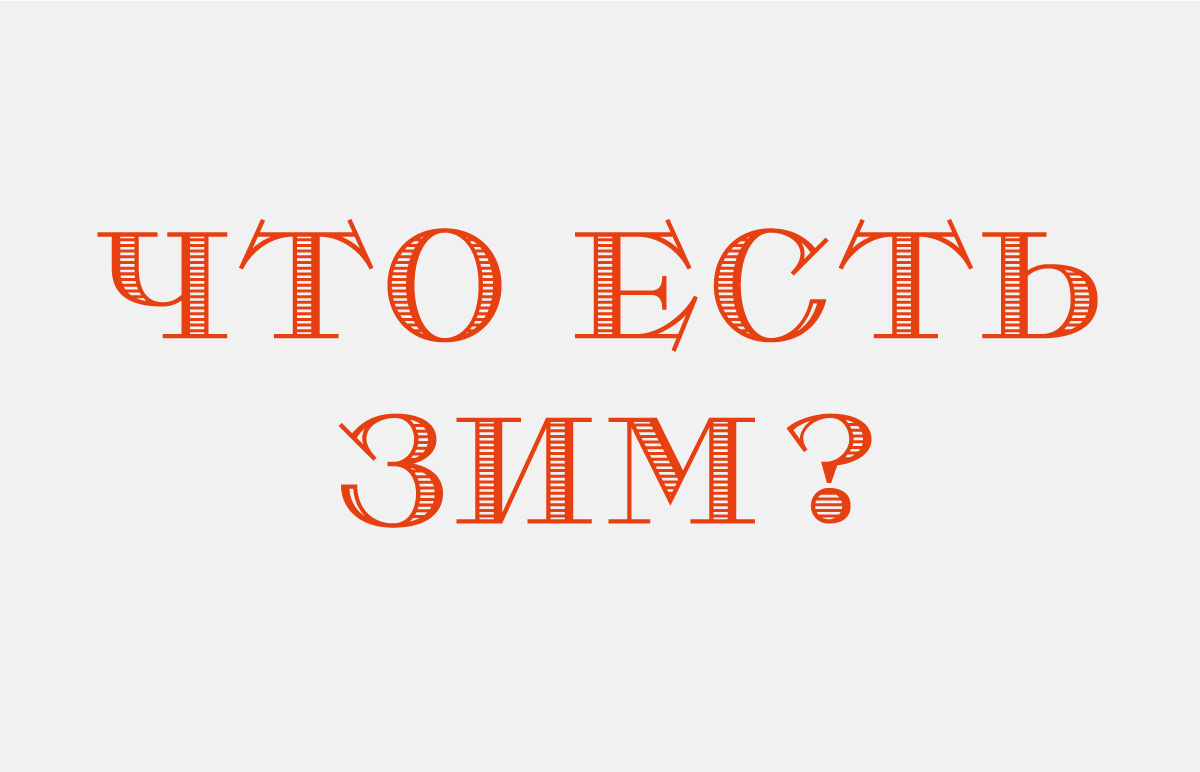
Конгрев как символ тирании
Книга Александра Лекае о легендарном детище Горьковского автомобильного завода — ГАЗ-12 «ЗИМ» — напоминает поэму, где всего с избытком: певучих строк о внешнем виде представительского автомобиля, исторического пафоса, вставных новелл о вожде, который, как и подобает истинному тирану, то казнит, то милует в зависимости от расположения духа. Однако, преодолевая пафос, постепенно приходишь к главному: это книга о времени и людях, которые верили в свою судьбу.
печатляющий красный том повествует не только о выдающемся советском инженере-конструкторе Андрее Александровиче Липгарте, о драматической истории создания автомобиля в жёстких условиях войны и мира, больше похожего на войну. Главным образом он рассказывает об одержимости ремеслом. Дело, в конце концов, не в блестящем, похожем на майского жука ЗИМе (который и сегодня вызывает восхищение не только у коллекционеров и любителей техники), а в той правде, которая через десятилетия оказалась выше любых политических вихрей, — правде последнего винтика в автомобиле или самого незначительного (на взгляд обывателя) узла на чертёжной кальке, над которым трудились и орденоносный конструктор Липгарт, и гениальные инженеры Борис Акимович Дехтяр и Владимир Никитич Носаков, и все рабочие завода.
В этом свете дизайн книги выглядит старательно выстроенной декорацией, призванной помочь читателю стать сопричастным тому времени. Собственно, такова и была идея издателя. В понимании Александра Лекае, рассказ должен был подкрепляться стилистически равными изобразительными деталями — от рисунка форзаца до последней наборной линейки.
Спектакль, разыгранный дизайнерами, оказался правдоподобен. Здесь нужно на минуту отвлечься и представить себе некоторые особенности имперского стиля эпохи диктатуры 1930–1950-х. Контраст помпезного и консервативного сталинского ампира по отношению к функционализму и новаторству 20-х годов позволяет нам довольно точно выявить визуальные приметы обеих эпох.
«Большой стиль» Cоветской империи, как правило, связывают триадой «греческая Античность — Рим — итальянский Ренессанс» (та же эстетика была характерна для Третьего рейха), но на самом деле ампир вобрал в себя куда больше: и готику, и модерн, и русское барокко, и даже конструктивизм. Так, в архитектуре мы видим крупные масштабы, склонность к впечатляющим ансамблям строений, предельную внимательность к строительному материалу, высочайшую степень декоративности (лепнина, бронза, дорогие сорта дерева), обязательные героические панно и мозаики.
В книжном дизайне ампир выражен обилием полиграфических и типографических изысков: отметим рисованные шрифты-антиквы на титульных листах, всевозможные наборные украшения, заставки, рамки, концовки, богато декорированные форзацы, суперобложки, инкрустацию, с трудом воспроизводимый ныне глубокий конгрев на роскошных переплётах и так далее. Типографические вещи культуры 2 (по Паперному) соревнуются между собой в пышности, словно на параде: кто ярче блеснёт позолотой, кто выше ляжет роскошным футляром на полках.
Однако для понимания дизайна книги Александра Лекае важно отметить не только внешний декор, но прежде всего внутренний стержень сталинского ампира. Этим стержнем является собственная история эпохи и стиля, которая пишется, подобно римским хроникам, почти параллельно с происходящим событием (известно, что римляне были довольно равнодушны к высокому искусству театра и поэзии, но дали миру лучших историков). В этом заключается идея создания вечного сооружения, автомобиля, книги.
И вот перед нами том, оформленный в узнаваемом ампирном духе. Несложно вообразить, что именно такой фолиант, например, могли писать и оформлять параллельно с проектированием ЗИМа и в последнюю ночь (перед презентацией Сталину) оборачивать тонкой бумагой.
технолог печати, типография «Принт-Маркет»
Когда мы искали подходящую бумагу, то сделали тесты на «Террапринт 90», однако партия сильно отличалась от образца: фактически бумага была белая, и требуемого эффекта достичь не удалось. Печать пятым прогоном тоже выглядела чересчур синтетически. Тогда мы решили использовать плотный офсетный лак желтоватого оттенка, применявшийся 5–6 лет назад для закрепления красок и борьбы с отмарыванием. Это старый технический лак, ему на смену давно пришли более прозрачные и не влияющие на колористику изображения сорта. Мы решили экономить на бумаге: взяли краснокамскую «меловку» с 92 % белизны, формата 70×100 и, подмешивая в густой офсетный лак разное (от 5 до 9 % сольвентной жёлтой краски), выкатали несколько проб, одна из которых устроила по колористике дизайнера и издателя.
Горизонтальная по формату книга закована в красный переплёт с конгревом и тиснением золотом (дизайнеры долго сверяли его покрытие с переплётами конца 40-х — начала 50-х годов). Мы видим нарядный форзац в три краски (красный, чёрный, золото), и торжественные титулы с центральной выключкой, и английские линейки, напоминающие о декоре книг издательства Academia середины 1930-х годов, и монолитные (будто гипсовые медальоны) буквицы, и ту самую мелованную бумагу с чуть желтоватым оттенком, и иллюстрации, проложенные калькой, и алое шёлковое ляссе, и, конечно же, шрифты.
В наборе книги использована гарнитура Академическая, которая в начале 1930-х успешно прошла стандартизацию гартовых шрифтов по ОСТ 1337 и вошла в ограниченный ассортимент шрифтов советской полиграфической промышленности. Тогда же рисунок отдельных знаков был несколько упрощён и, кроме того, гарнитуру пополнили новыми кеглями и полужирным начертанием. В советское время Академическая использовалась во множестве изданий и стала своего рода «фирменным» шрифтом многих книжных серий (к примеру, легендарной «Библиотеки поэта»). Гарнитура появилась на свет ещё до революции благодаря заказу типографии Императорской академии наук словолитне Бертольда в 1910-х годах. Основой для неё послужил шрифт Sorbonne, малоконтрастная антиква, нарезанная Бертольдом в Берлине в 1905 году и весьма популярная в то время. Она, в свою очередь, вела происхождение от гарнитуры Cheltenham фирмы American Type Founders, 1896 (дизайнеры Бертрам Гудхью и Моррис Бентон). Кириллица Академической гарнитуры своеобразно стилизована неизвестным художником под шрифты типографии Академии наук XVIII века со всеми характерными деталями букв гражданского шрифта, введённого реформой Петра I.